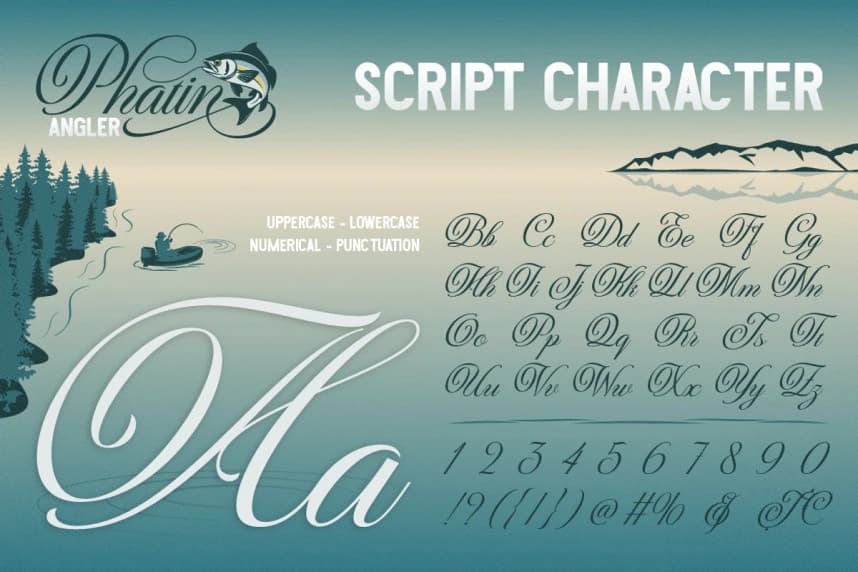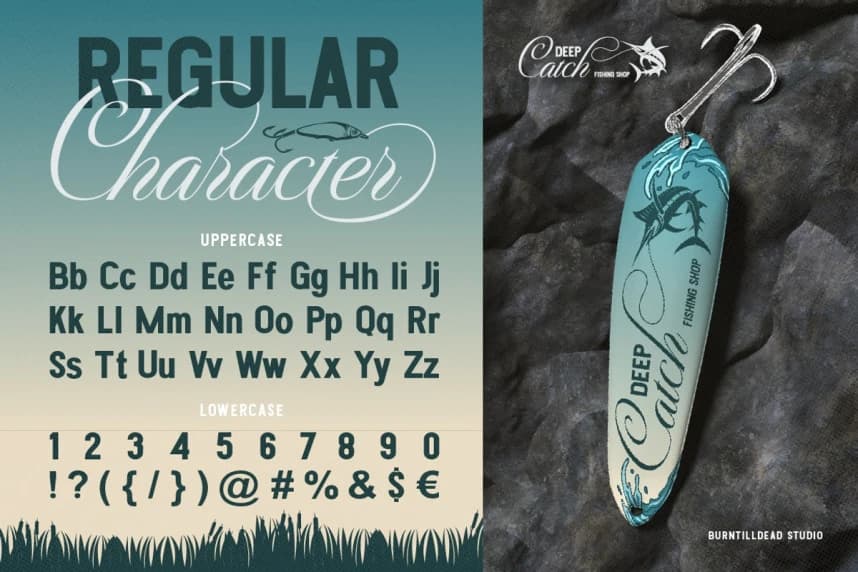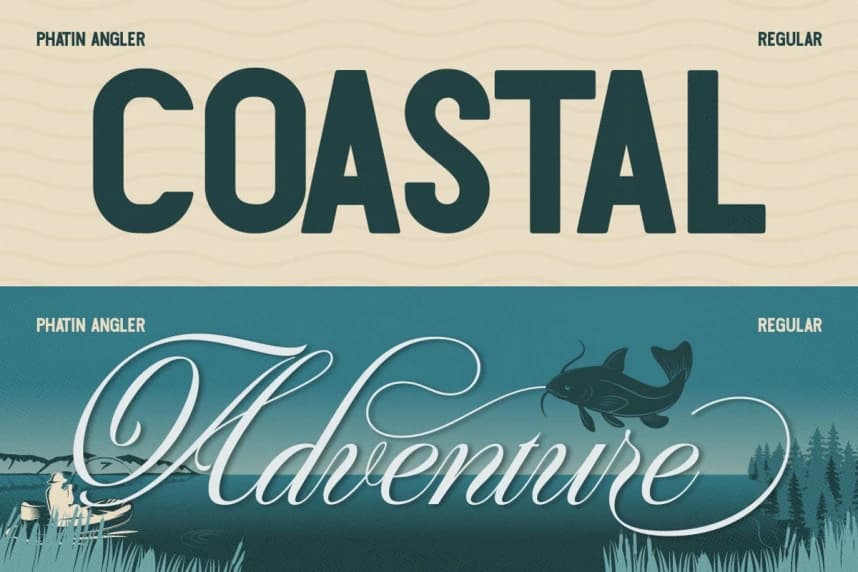
Phatin Angler Font
Phatin Angler Font, balıkçılık temalı bir yazı tipi ikilisidir ve iki farklı stili tek mükemmel dengeli bir paket halinde birleştirir: zarif kaligrafik darbeler içeren akan bir el yazısı stili ve kalın bir normal stil. Her iki stil de birbirini tamamlayacak şekilde özenle tasarlanmıştır ve zengin, g
Phatin Angler Font, balık temalı bir yazı tipi ikilisidir ve iki ayrı stili tek, tamamen dengeli bir paket halinde birleştirir: zarif kaligrafik çizgilere sahip akıcı bir el yazısı stili ve kalın bir normal stil. Her iki stil de birbirini tamamlayacak şekilde özenle tasarlanmıştır, zengin, görsel olarak etkileyici tipografi yaratır.
Phatin Angler
Phatin Angler Regular